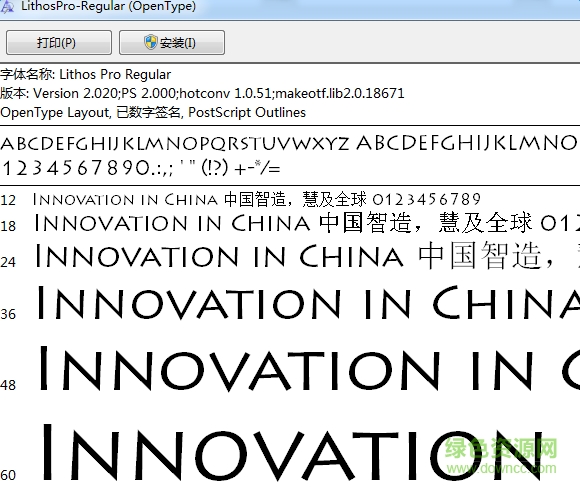
LITHOS英文字體
LITHOS字體是一款超好用的個(gè)性英文字體,該字體非常正式,適用于多個(gè)設(shè)計(jì)領(lǐng)域,讓用戶能夠輕松得到自己所需要的宣傳效果。需要的朋友趕快來(lái)綠色資源網(wǎng)下載使用吧!
LITHOS字體是一款個(gè)性字體,該字體十分飄逸,彰顯了自己的個(gè)性,有喜歡的朋友可以來(lái)綠色資源網(wǎng)下載使用!